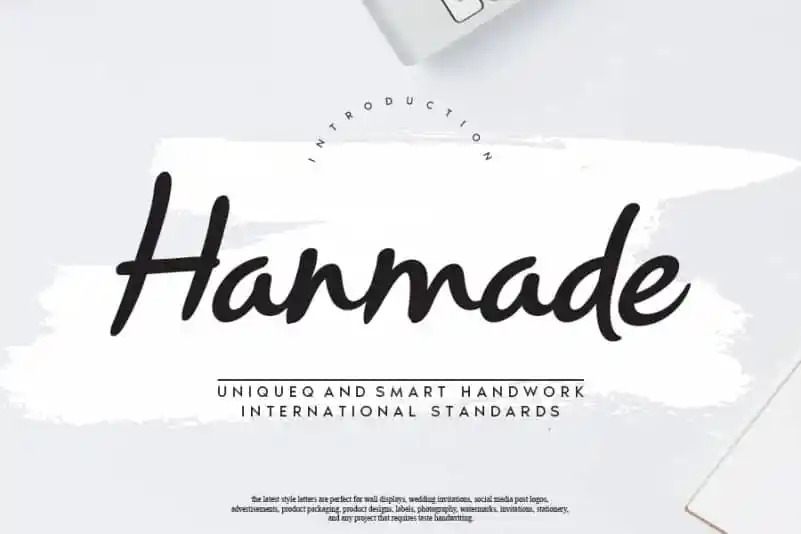
Hanmade Script Font – Download Grátis
A Hanmade Script Font é uma fonte script fluente que retrata a elegância do traçado livre. Essa fonte perfeita para seus projetos favoritos tem um estilo distintivo e eterno, tornando-a perfeita para criar designs excepcionais. Suas letras fluidas parecem autênticas escrituras manuscritas, com uma personalidade própria que vai remeter sua visão de design ao público. Seu traçado delicado permite que as letras se movam livremente, criando um impacto visual único e emocionante em qualquer projeto gráfico. Estamos ansiosos para ver como você a usa em seus projetos!